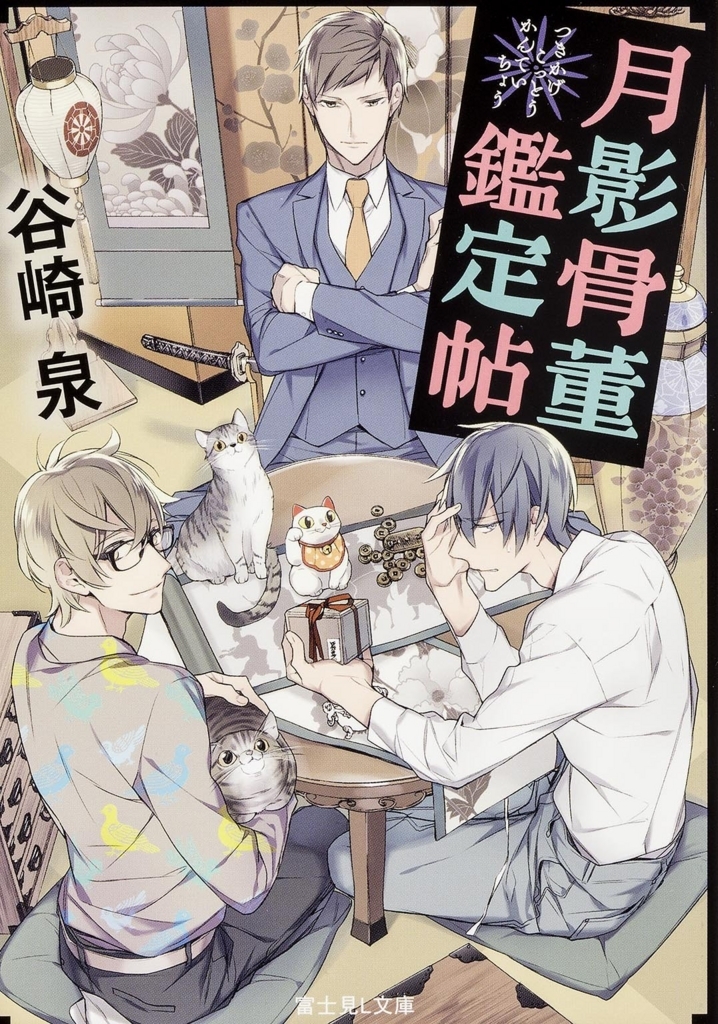
「月影骨董鑑定帖」シリーズ
「月影骨董鑑定帖シリーズ」は著者・谷崎泉、イラスト・宝井理人による東京都にある谷中、月影寺に建つ日本家屋に住む骨董鑑定に才を持つ白藤晴と居候の骨董オタク・宇多蒼一郎を主人公としたミステリー小説。
本筋はミステリー小説で、設定からして漂うBL臭は風味なのか、ガチ路線なのか。
それは読んでみないと分からないが、夜の公園に武術家二人なら勝負でしょうと言えるが、谷中の月影寺に建つ日本家屋に男二人なら腐っているでしょうとしか言えない。
現在、第3弾まで刊行されている。
月影骨董鑑定帖シリーズのタイトルのフォントにダイナフォント古籍黒檀が採用
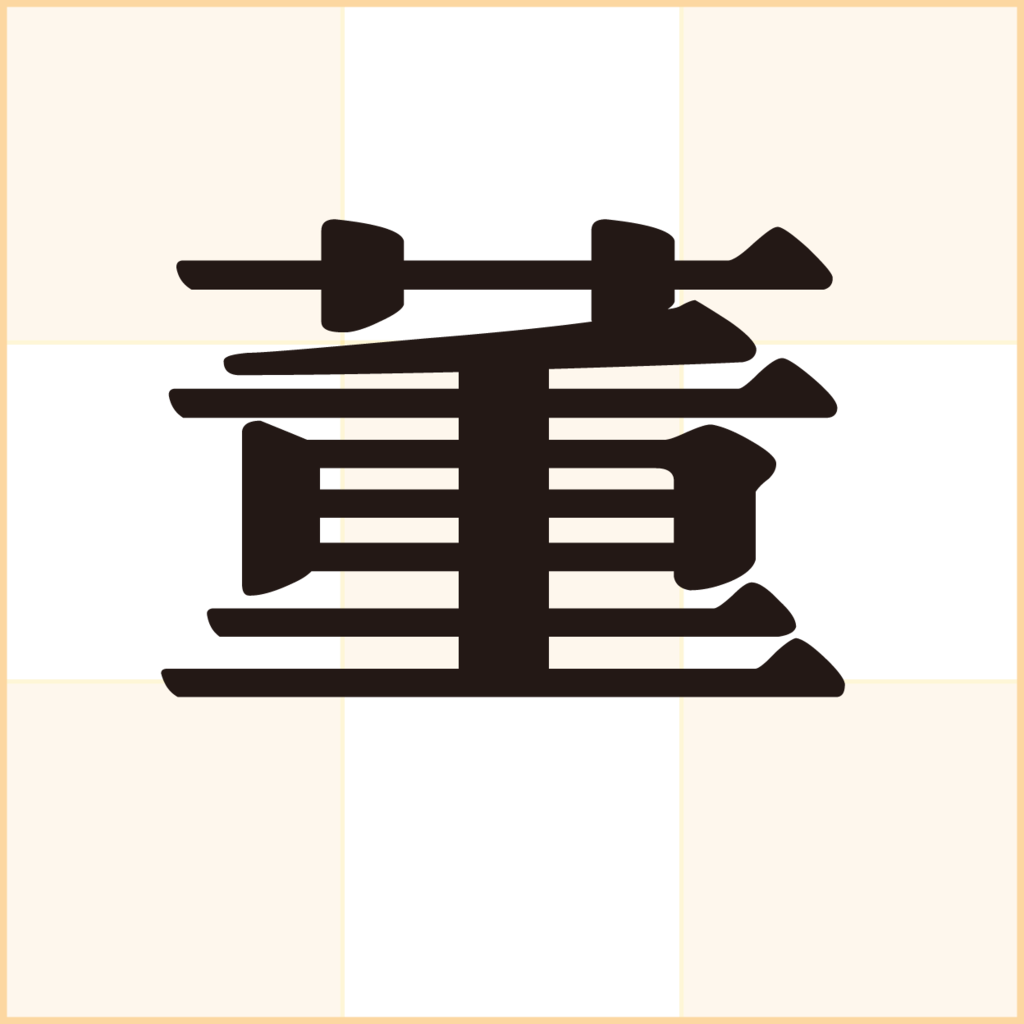
ライト文芸系文庫レーベル「富士見L文庫」から出版されている「月影骨董鑑定帖シリーズ」のタイトルに「ダイナフォント 古籍黒檀」が採用されている。
古籍黒檀
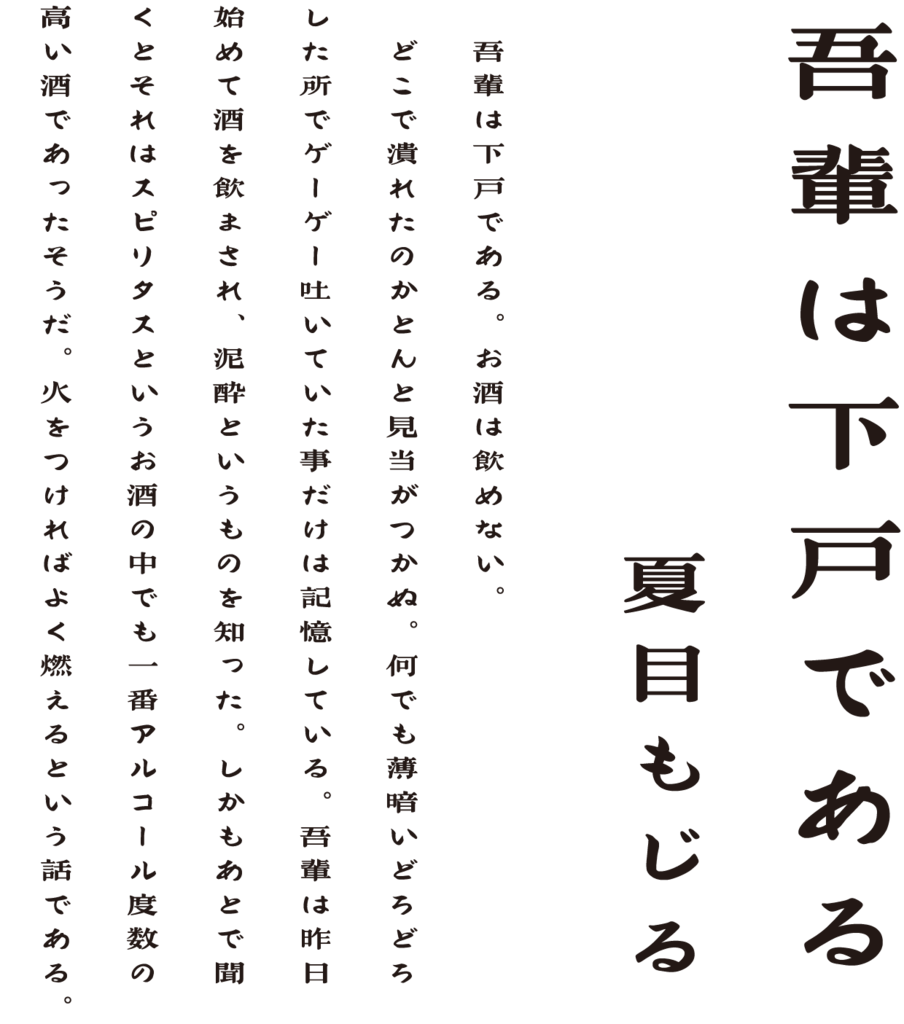
中国の古籍「范伯子集」の書帖をもとに開発された書体。「范伯子集」の文字は扁平な字形に重厚なストロークが特徴で、転折が力強く彫刻の質感のような雰囲気が溢れている。